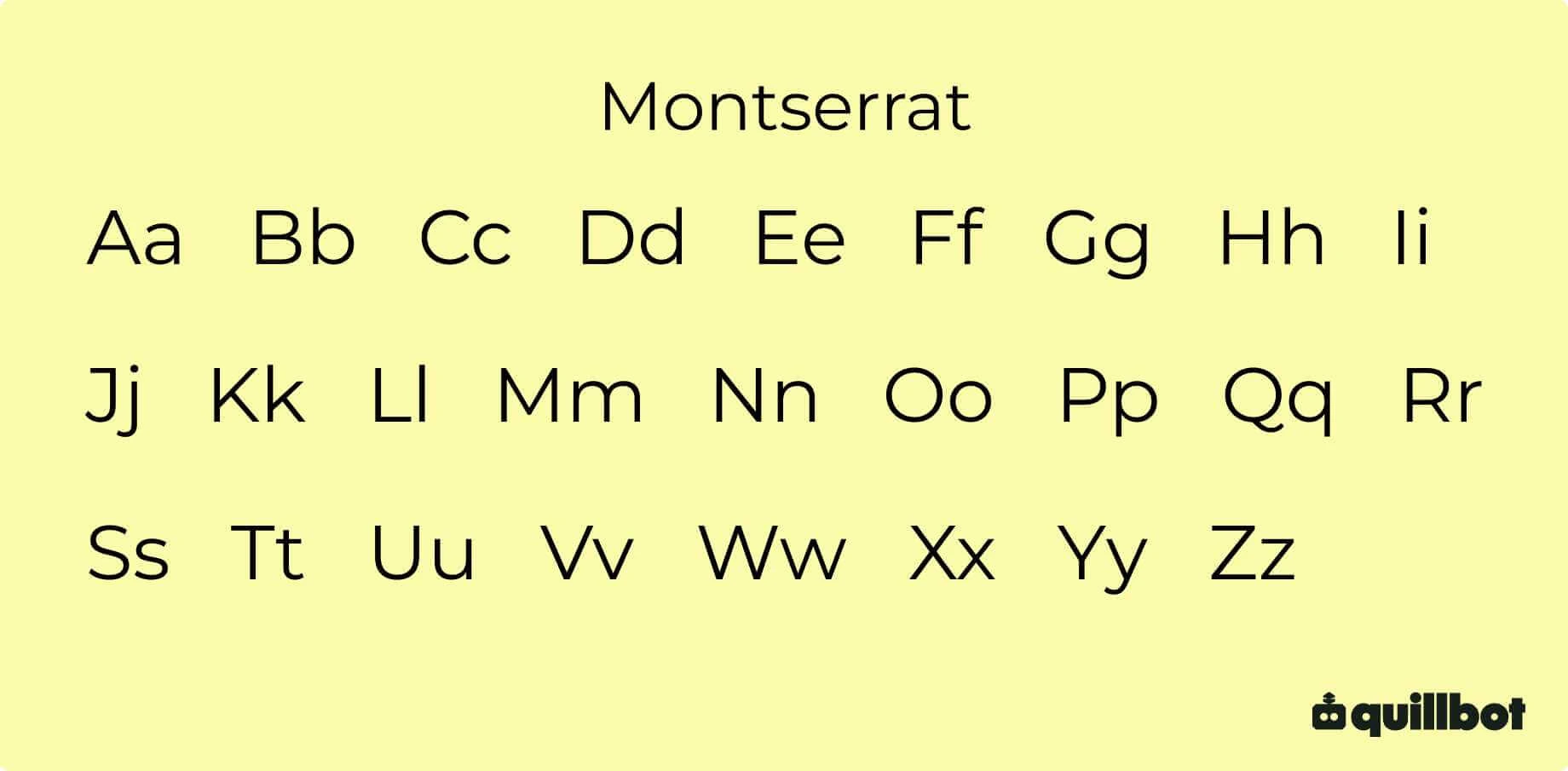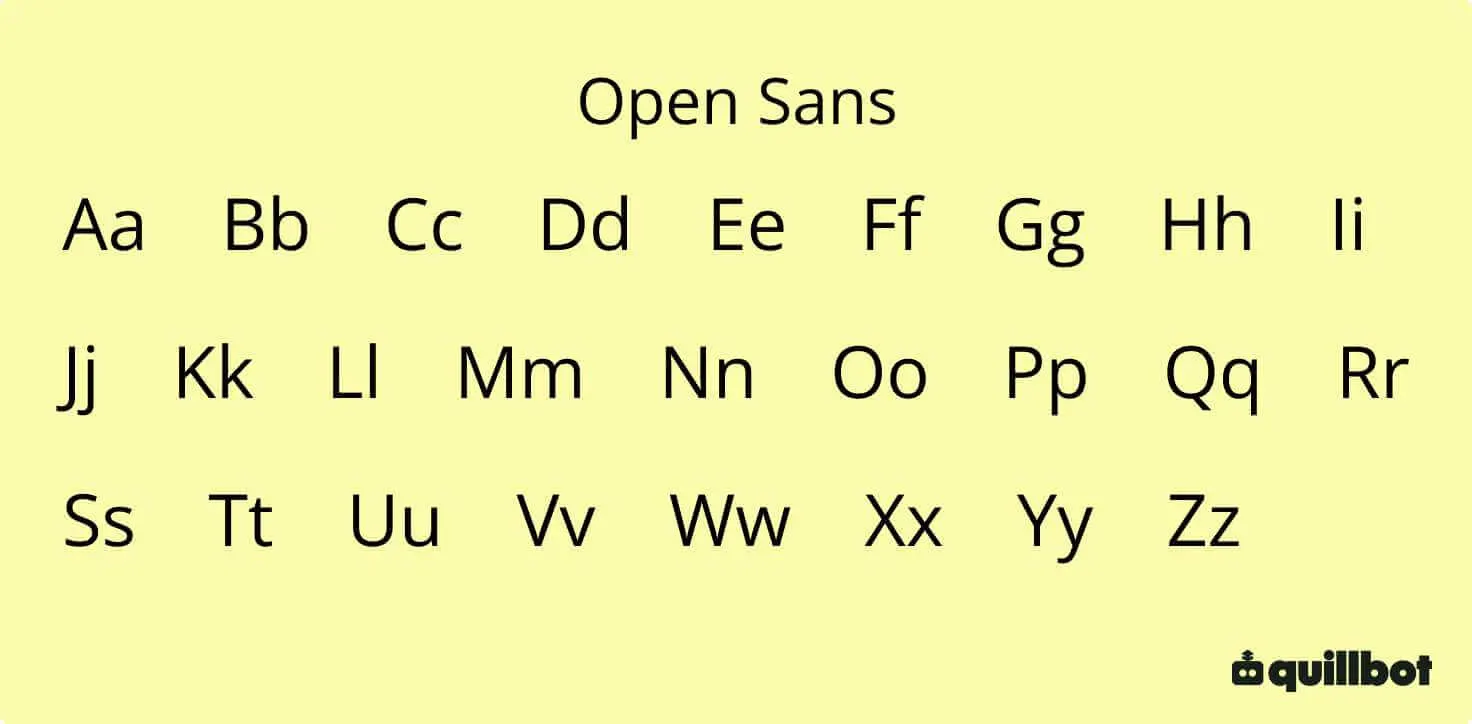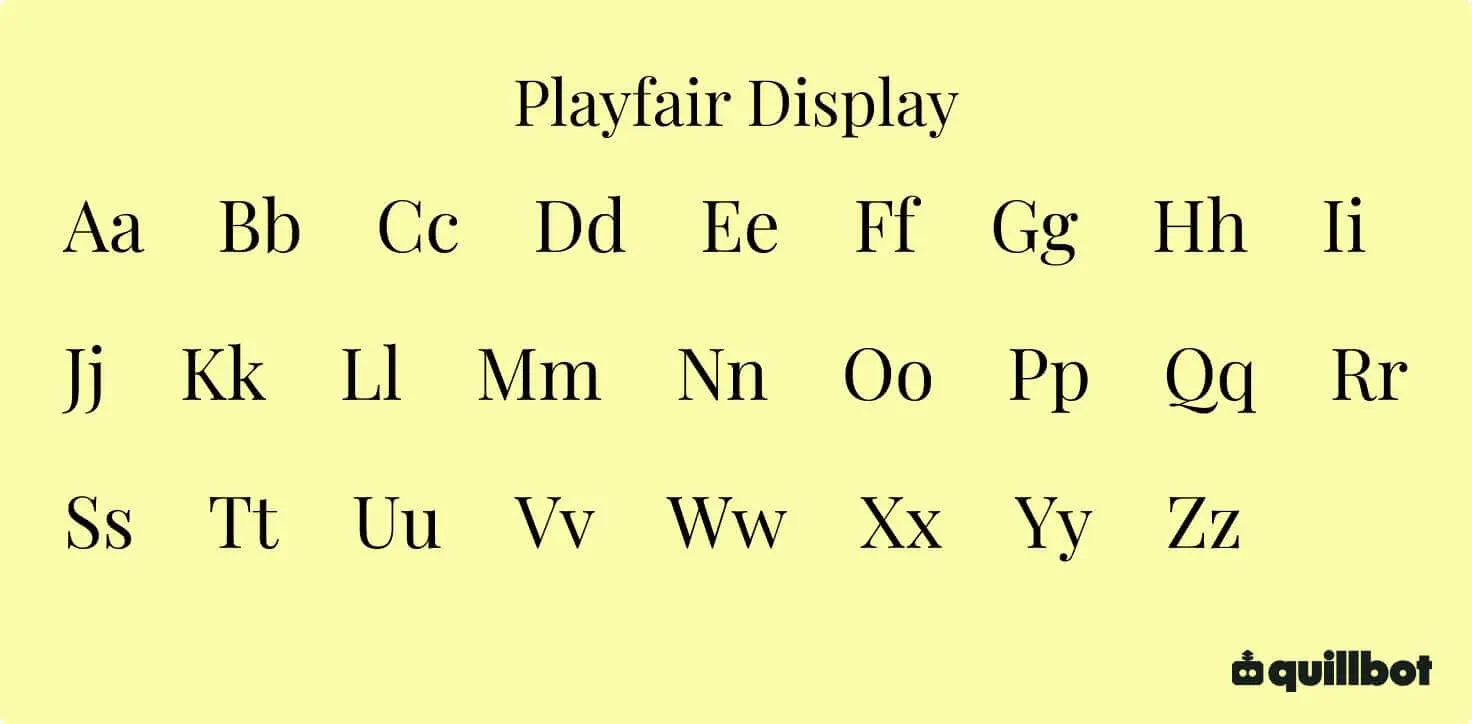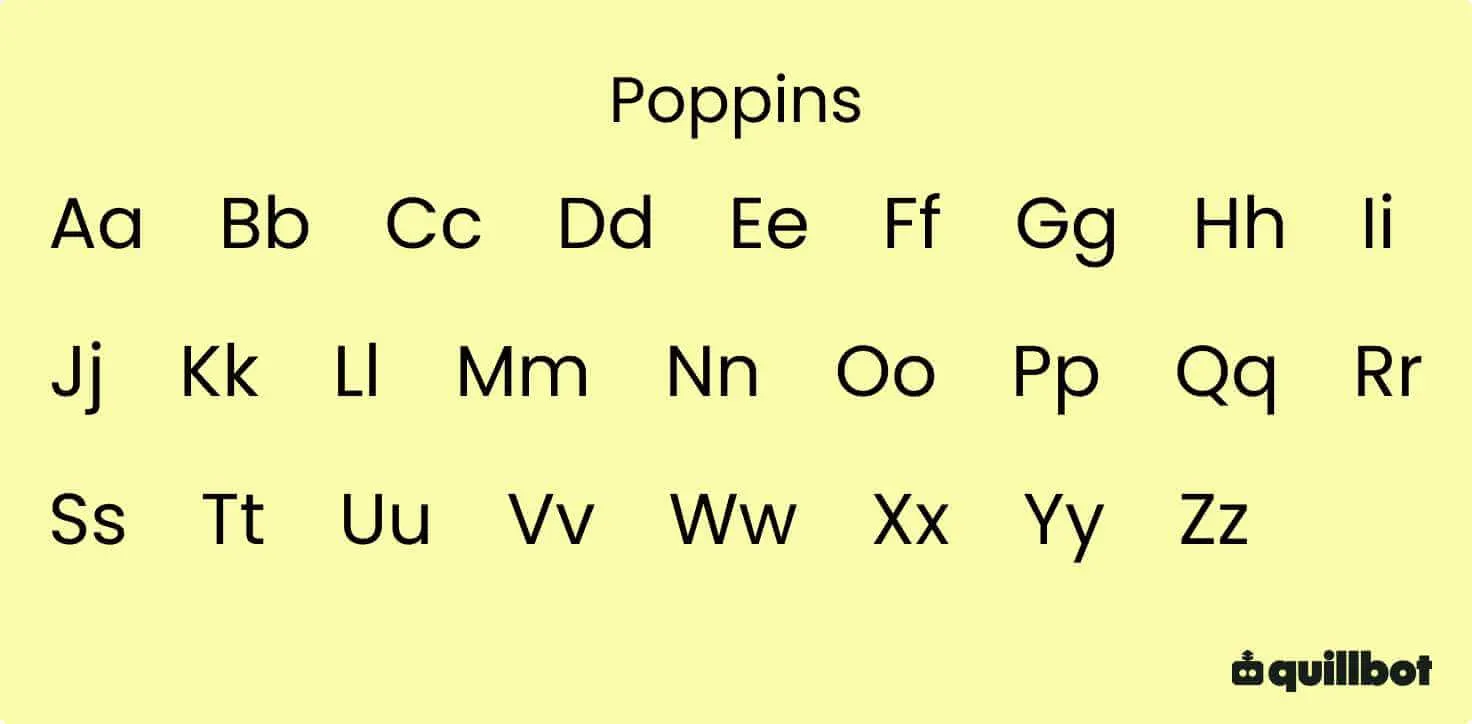
Uma fonte para logo não é simplesmente uma escolha estética. Trata-se de encontrar letras que transmitam a identidade da marca, com um visual único, gerando uma resposta emocional específica.
Criar logotipos é uma mistura de arte e ciência. É gerar um design tipográfico original e único que comunica, por meio da forma e do conteúdo, uma expressão visual marcante, ao mesmo tempo em que capta as pessoas.
As letras gregas não só foram importantes na história da escrita, como também deixaram um impacto cultural profundo.
Este alfabeto, que surgiu do sistema fenício por volta do século VIII a.C., introduziu vogais, algo que não existia nos sistemas anteriores, permitindo uma representação muito mais precisa e clara da linguagem falada.
As letras gregas foram a base para a criação do alfabeto latino, usado em grande parte do mundo ocidental.
Atualmente, as letras gregas ainda estão presentes em áreas como matemática, física e estatística, bem como em outros contextos acadêmicos e culturais.
NotaO termo “alfabeto” é um helenismo que vem do grego alphábētos.
Este nome foi formado a partir da união das letras gregas alfa (α) e beta (β) — as duas primeiras do alfabeto —, ou seja, usando-as para nomear o sistema.
Isso se repete no termo latino “abecedário” (a, b, c, d). “Abecedário” vem do latim abecedarium.
Principais pontos
O alfabeto grego tem 24 letras e surgiu por volta do século VIII a.C., a partir do sistema fenício, destacando-se pela introdução de caracteres específicos para representar vogais.
As letras gregas influenciaram profundamente a escrita ocidental, servindo de base para alfabetos como o latino e o cirílico e contribuindo para a preservação e transmissão do conhecimento.
Atualmente, letras como alfa (Α, α), beta (Β, β), delta (Δ, δ), pi (Π, π), sigma (Σ, σ) e ômega (Ω, ω) continuam presentes em áreas como matemática, física, astronomia, medicina e tecnologia.
Além da ciência, as 24 letras gregas aparecem em diversos contextos culturais e sociais, desde nomes de gerações e variantes de vírus até fraternidades, redes sociais e símbolos de áreas acadêmicas.
Letras diferentes são formas estilizadas, decorativas ou alternativas de representar as letras do alfabeto.
Elas podem apresentar variações de formato, espessura, inclinação e ornamentação, criando efeitos visuais que personalizam textos e designs.
Na internet, a expressão “letras diferentes” é muito utilizada para se referir a caracteres especiais que podem ser copiados e colados em redes sociais, mensagens e outros espaços digitais.
Além dos caracteres usados na internet, as letras diferentes também podem ser criadas por meio da tipografia, da caligrafia e do lettering.
NotaNa internet, muitas letras diferentes para copiar e colar são, na realidade, caracteres Unicode.
Unicode é um padrão internacional de codificação que atribui um código único a caracteres, símbolos e sinais de escrita, permitindo que eles sejam reconhecidos e exibidos de forma consistente em computadores, celulares e outros dispositivos.
No caso das chamadas “letras diferentes”: o Unicode é importante porque muitos estilos que parecem fontes diferentes são, na verdade, caracteres distintos.
Eles parecem versões estilizadas da mesma letra, mas são caracteres Unicode diferentes. É por isso que muitas dessas letras diferentes podem ser copiadas e coladas em redes sociais sem instalar uma fonte.
Principais pontos
Letras diferentes são formas estilizadas ou alternativas de representar caracteres, usadas para personalizar textos, nicks, redes sociais e projetos de design.
Na internet, muitas letras que parecem fontes diferentes são, na verdade, caracteres Unicode, que podem ser copiados e colados sem a instalação de novas fontes.
A escolha do estilo deve considerar legibilidade, contexto, harmonia, acessibilidade e compatibilidade com diferentes plataformas e dispositivos.
Geradores de letras diferentes facilitam a criação de textos estilizados, oferecendo opções como letras cursivas, góticas, serifadas, em negrito e outros estilos visuais.
As letras chinesas, ou caracteres chineses, conhecidos como hanzi — 汉字 —, não são simplesmente letras, mas logogramas que representam morfemas ou conceitos — como fogo ou sol — em vez de sons fonéticos individuais — [a] ou [b].
É um dos sistemas de escrita mais antigos do mundo.
Os caracteres chineses, ou letras chinesas, têm uma história que abrange mais de 3.000 anos. Sua origem está nos ossos oraculares, vestígios arqueológicos que contêm a forma mais antiga de escrita chinesa, datando da Dinastia Shang, entre 1600 e 1046 a.C.
A arte do grafite reúne diferentes técnicas e estilos, como Tag, Bubble Letters, Wildstyle, Block Letters, 3D e Tag Reto, utilizando tanto tinta spray quanto ferramentas digitais.
Hoje, as letras de grafite ultrapassam os muros das cidades, influenciando áreas como design gráfico, moda, publicidade, mídias sociais, arte contemporânea e cultura pop.
Entender a história, as técnicas e os estilos do grafite ajuda a reconhecer sua importância como uma das expressões mais marcantes da comunicação visual urbana.